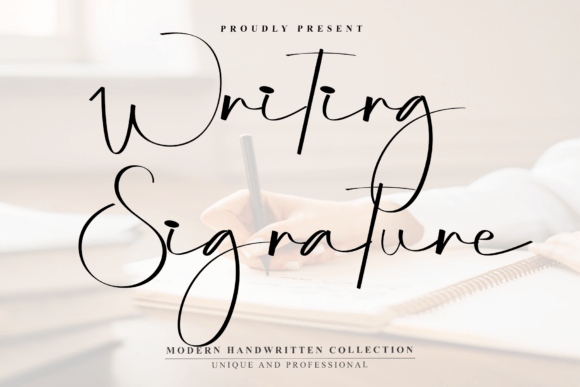
Writing Signature
์˜ฌ๋ฐ”๋ฅธ ๋””์ž์ธ ์š”์†Œ๋ฅผ ์ฐพ๋Š” ๊ฒƒ์€ ์–ด๋ ค์šธ ์ˆ˜ ์žˆ์ง€๋งŒ Writing Signature๋Š” ์ž‘์—…์„ ์ฆ‰์‹œ ํ–ฅ์ƒ์‹œํ‚ค๋Š” ๋›ฐ์–ด๋‚œ ์ปฌ๋ ‰์…˜์„ ์ œ๊ณตํ•ฉ๋‹ˆ๋‹ค.
POD(์ฃผ๋ฌธํ˜• ์ธ์‡„) ์ œํ’ˆ, ๊ฒฐํ˜ผ์‹ ์ดˆ๋Œ€์žฅ ๋˜๋Š” ์†Œ์…œ ๋ฏธ๋””์–ด ๊ทธ๋ž˜ํ”ฝ์„ ๋งŒ๋“ค ๋•Œ Writing Signature๋Š” ์ด์ƒ์ ์ธ ์„ ํƒ์ž…๋‹ˆ๋‹ค.